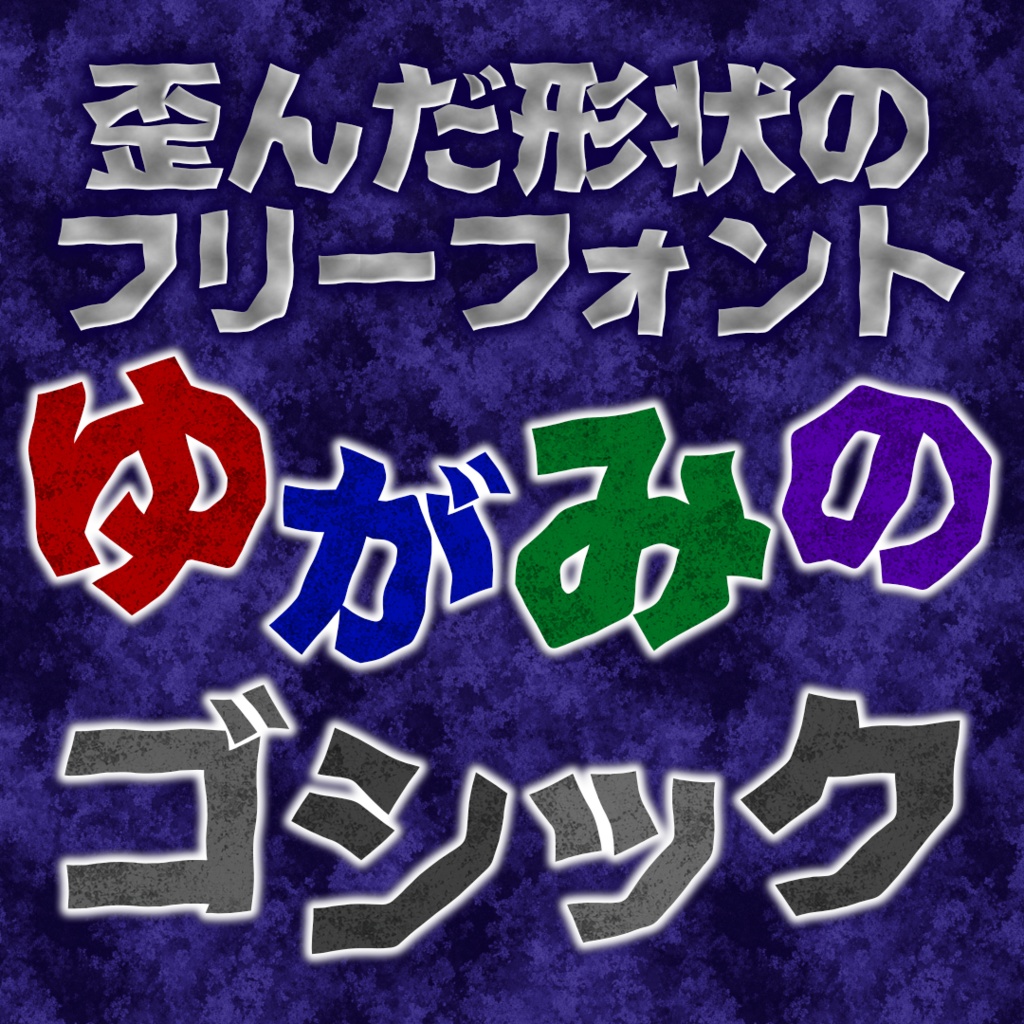
ゆがみのゴシック【フリーフォント】
ゆがみのゴシック 概要 当フォントは「源暎エムゴBlack」に歪み加工を追加したフォントです。 中身は同じですが、投げ銭版もございます。ご支援いただけましたら幸いです。 ライセンス 当フォントはSIL Open Font License1.1の下で公開いたします。 個人利用・商用利用にかかわらず無償で使用可能です。 SILライセンスにつきましては以下をご確認ください。 ライセンス原文 http://scripts.sil.org/OFL ライセンス原文日本語サイト https://licenses.opensource.jp/OFL-1.1/OFL-1.1.html ライセンスざっくり解説 https://tanukifont.com/sil/ 免責事項 当フォントの使用に関しては全て無保証とさせていただきます。 謝辞 全ての関係者の皆様に深くお礼申し上げます。 源暎エムゴ https://okoneya.jp/font/genei-m-gothic.html 詳細 お問い合わせ等ございましたらBOOTHの「ショップへのお問い合わせ」よりお願い致します。 横太明朝 制作:やっちゃん https://yattyann.booth.pm/ フォント公開・利用規約制定 2026年4月10日